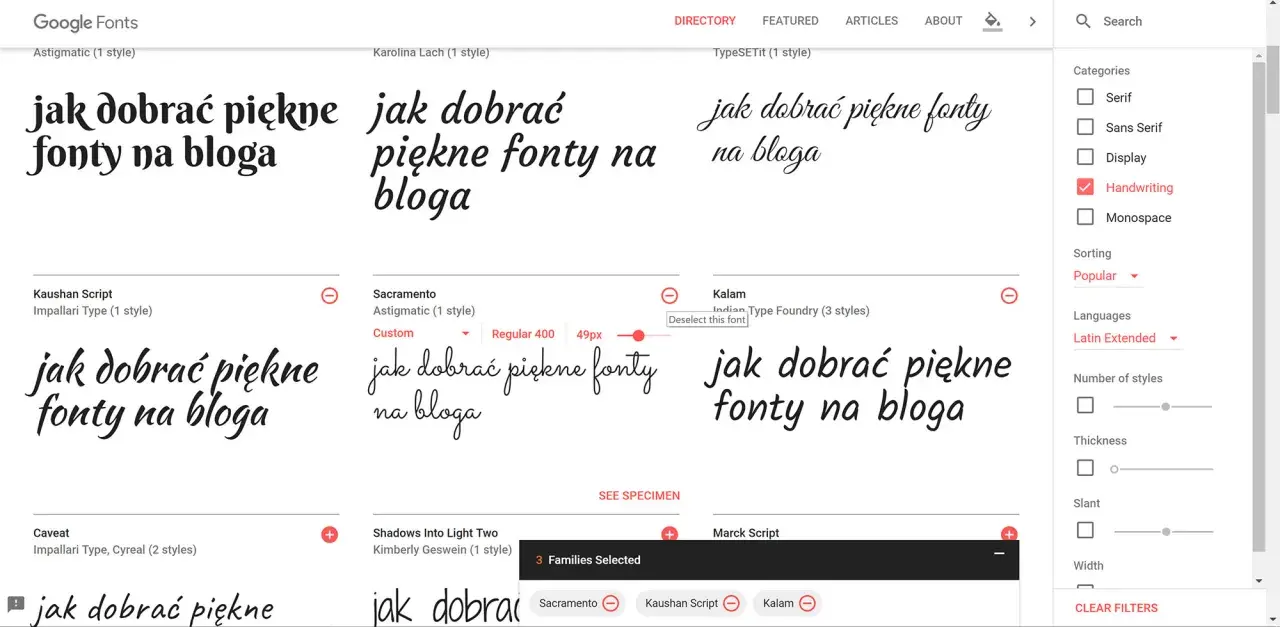
Najważniejsze rzeczy, które warto wiedzieć od razu
- Większość generatorów nie tworzy klasycznych fontów, tylko stylizowane znaki Unicode albo obrazy z tekstem.
- Najlepiej sprawdzają się krótkie formy: bio, hasła, nagłówki, nazwy promocji i podpisy do postów.
- Polskie znaki to pierwszy test jakości narzędzia, bo nie każdy styl obsługuje je poprawnie.
- Na telefonie wszystko wygląda inaczej, więc podgląd mobilny ma większe znaczenie niż sam efekt w przeglądarce.
- W marketingu lokalnym taki tekst działa jako akcent, nie jako główny nośnik całej treści.
- Największy błąd to używanie dekoracji tam, gdzie ważniejsze są czytelność, kontrast i szybkie zrozumienie oferty.
Jak działają takie narzędzia i co naprawdę kopiujesz
Najważniejsza rzecz, którą warto zrozumieć na starcie, jest prosta: wielu generatorów nie zmienia czcionki w klasycznym sensie. Zamiast tego przepisują litery na podobne znaki Unicode, czyli na osobne symbole, które wizualnie przypominają kursywę, pismo odręczne, frakturę, kapitaliki albo litery w kółkach. Dzięki temu efekt da się skopiować i wkleić do bio, opisu profilu czy wiadomości bez instalowania czegokolwiek.Druga grupa narzędzi działa inaczej. Tworzy dekoracyjny napis jako obraz, więc masz większą kontrolę nad kolorem, cieniem, obrysem czy układem, ale tracisz elastyczność edycji. Taki tekst nie zachowuje się już jak zwykły zapis, tylko jak grafika, więc nie zawsze da się go łatwo poprawić, przetłumaczyć albo automatycznie dostosować do różnych formatów.
To rozróżnienie jest ważne, bo od niego zależy, czy efekt będzie działał w praktyce. Jeśli chcesz wkleić stylizowany podpis do social mediów, lepszy będzie tekst Unicode. Jeśli tworzysz baner, miniaturę albo grafikę promocyjną, wygodniejsze bywa narzędzie, które traktuje napis jak element projektu. Gdy to sobie uporządkujesz, wybór dalszych opcji staje się dużo prostszy.
Kiedy lepiej wybrać generator tekstu, a kiedy narzędzie graficzne
W codziennym użyciu widzę trzy sensowne ścieżki i każda z nich rozwiązuje trochę inny problem. Nie ma jednego najlepszego rozwiązania, bo wszystko zależy od tego, czy chcesz skopiować efekt do pola tekstowego, czy zbudować go jako część grafiki.
| Typ narzędzia | Najlepsze zastosowanie | Plusy | Ograniczenia |
|---|---|---|---|
| Generator znaków Unicode | Bio, podpis, krótki nagłówek, nazwa promocji | Szybki, prosty, zwykle działa bez instalacji | Nie każdy styl obsługuje wszystkie znaki, szczególnie polskie |
| Generator napisów jako obraz | Baner, miniatura, grafika do posta, okładka wydarzenia | Większa kontrola nad wyglądem i kompozycją | Trudniejsza edycja, tekst nie zachowuje się jak zwykły zapis |
| Edytor projektowy z fontami | Spójne materiały marki, kampanie, zestawy grafik | Najlepsza kontrola nad całą identyfikacją wizualną | Wymaga więcej czasu i podstawowego obycia z projektem |
Na co zwracam uwagę przed użyciem
Przy takich narzędziach nie interesuje mnie liczba stylów sama w sobie. Ważniejsze jest to, czy konkretne rozwiązanie będzie użyteczne po stronie odbiorcy. Zwykle sprawdzam kilka rzeczy, bo to one odróżniają wygodny generator od zabawki, która dobrze wygląda tylko w podglądzie.
- Polskie znaki - jeśli narzędzie gubi ą, ę, ł albo zamienia je w przypadkowe znaki, to w polskim biznesie jest to realny problem, a nie drobiazg.
- Podgląd na telefonie - efekt, który wygląda dobrze na dużym ekranie, potrafi być męczący w aplikacji mobilnej.
- Jednoznaczny copy-paste - tekst powinien dać się skopiować bez dodatkowych spacji, dziwnych separatorów i znaków, które psują układ.
- Brak watermarków i ograniczeń - przy prostych zastosowaniach reklamowych darmowe narzędzie z nachalnym oznaczeniem bywa po prostu słabym wyborem.
- Zakres stylów - nie potrzebuję setek wariantów, jeśli większość z nich wygląda podobnie; wolę kilka sensownych opcji niż ścianę niemal identycznych efektów.
- Tempo działania - jeśli mam przygotować materiał na szybko, liczy się narzędzie, które reaguje natychmiast, a nie po kilku przeładowaniach.
W praktyce najczęściej sprawdzają się proste generatory znaków i narzędzia graficzne, które pozwalają od razu zobaczyć wynik. Dobrze prowadzone strony tego typu, takie jak proste generatory stylizowanego tekstu, stawiają na natychmiastowy efekt i kopiowanie jednym kliknięciem. Jeśli jednak zależy Ci na bardziej kontrolowanym projekcie, lepiej przejść do narzędzi, które traktują tekst jako część całej kompozycji. To prowadzi już prosto do zastosowań, gdzie dekoracja ma realnie wspierać marketing.
Gdzie taki tekst naprawdę pomaga firmie lokalnej
W lokalnym marketingu dekoracyjny tekst działa najlepiej tam, gdzie ma przyciągnąć wzrok w kilka sekund, ale nie musi dźwigać całej informacji. Nie używam go jako zamiennika porządnej komunikacji, tylko jako akcent, który porządkuje hierarchię treści.
| Miejsce użycia | Co daje | Jak używać rozsądnie |
|---|---|---|
| Bio profilu | Szybciej pokazuje charakter marki | Stylizuj tylko nazwę lub jedną linię, resztę zostaw prostą |
| Post o promocji | Pomaga wyróżnić rabat, datę albo hasło kampanii | Użyj jednego mocnego akcentu, nie całego akapitu |
| Grafika wydarzenia | Buduje klimat i od razu komunikuje charakter akcji | Połącz ozdobny napis z prostą informacją o miejscu i terminie |
Jeżeli zależy Ci na spójnym wizerunku, trzymaj się jednej estetyki dla całej kampanii i nie mieszaj zbyt wielu dekoracyjnych rozwiązań. To nie ograniczenie, tylko sposób na to, żeby wyróżnienie było kontrolowane. Właśnie tak używałbym takich narzędzi w praktyce: szybko, oszczędnie i z myślą o odbiorcy, który ma od razu wiedzieć, co mu proponujesz.